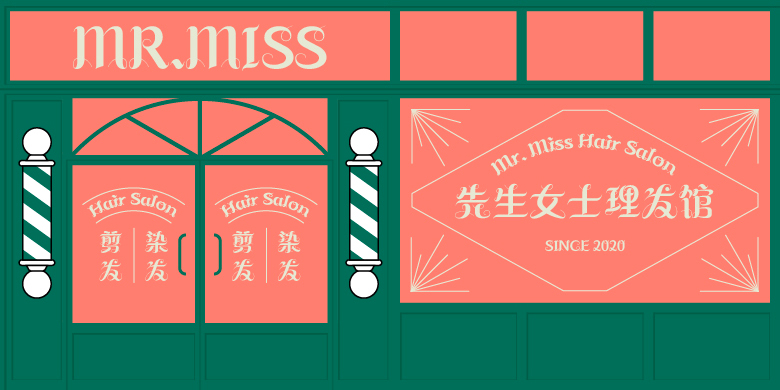
方正纤舞体
纤舞体是以拉丁文“Script”形态演绎的中文花写字体。“Script”字体源远流长,在西方非常普遍和流行,但在笔画繁复的中文字体中演绎时,难度甚高。作者以惊人的毅力,用了两年多时间终于攻克完成 “纤舞体”创作。纤舞体风姿绰约,曼妙动人,适合高档时装、化妆品、手袋、鞋类等包装宣传以及纤体美容类产品宣传,也适合生日卡、情人卡、圣诞卡和各种贺卡设计等等。